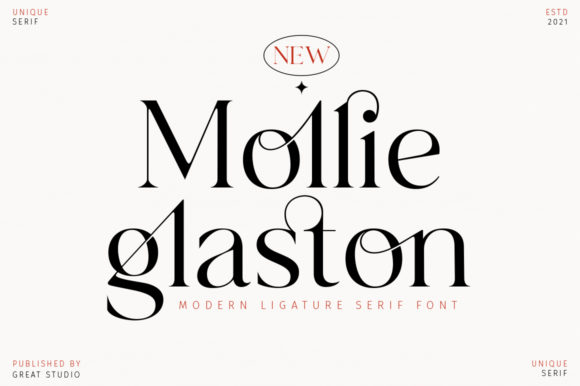
Mollie Glaston - это современный и четкий шрифт с засечкой.
Этот восхитительный шрифт может быть использован для различных целей, таких как логотипы, свадебные приглашения, заголовки, футболки, фирменные бланки, вывески, этикетки, новости, плакаты, значки и многое другое.